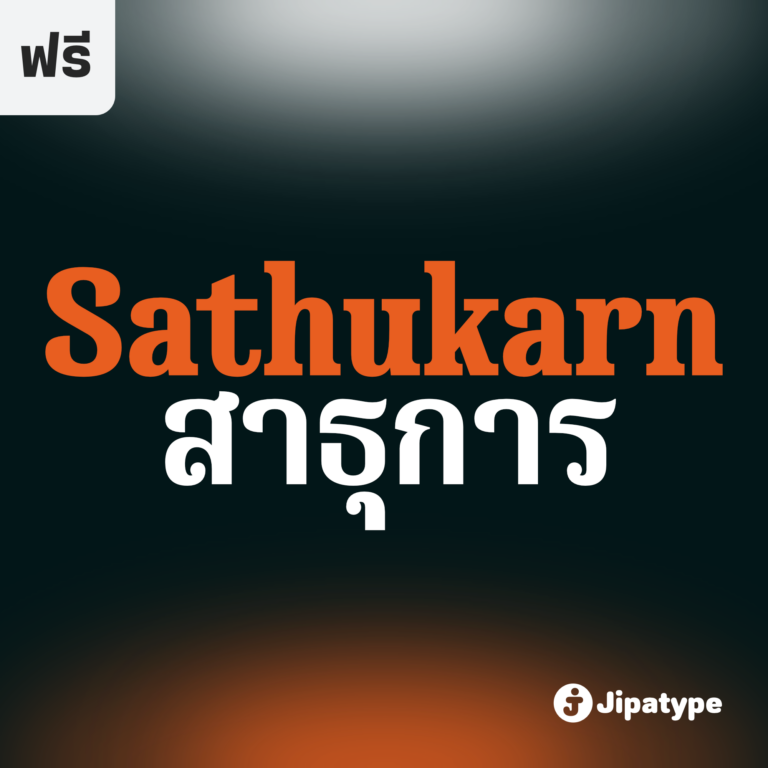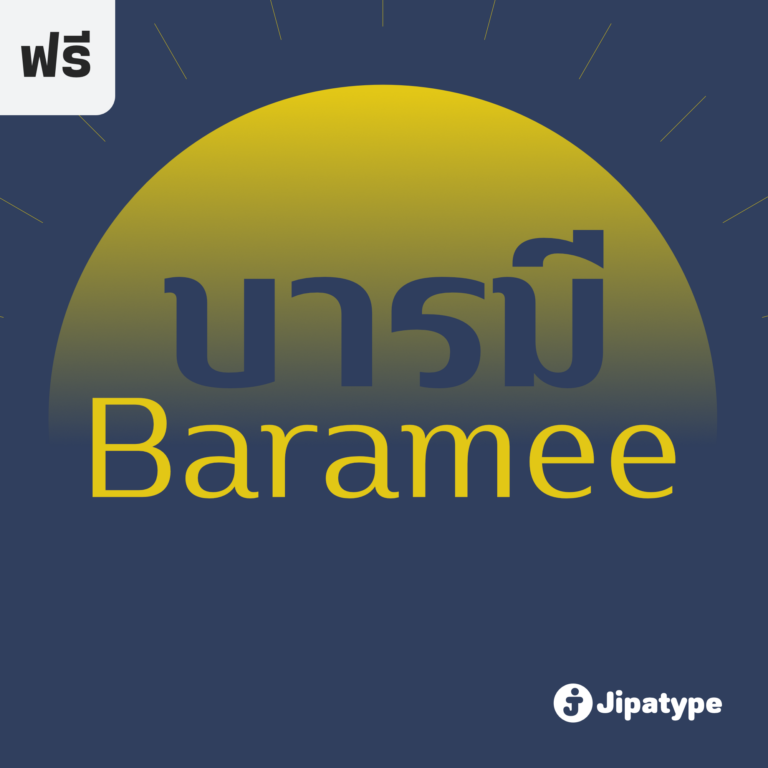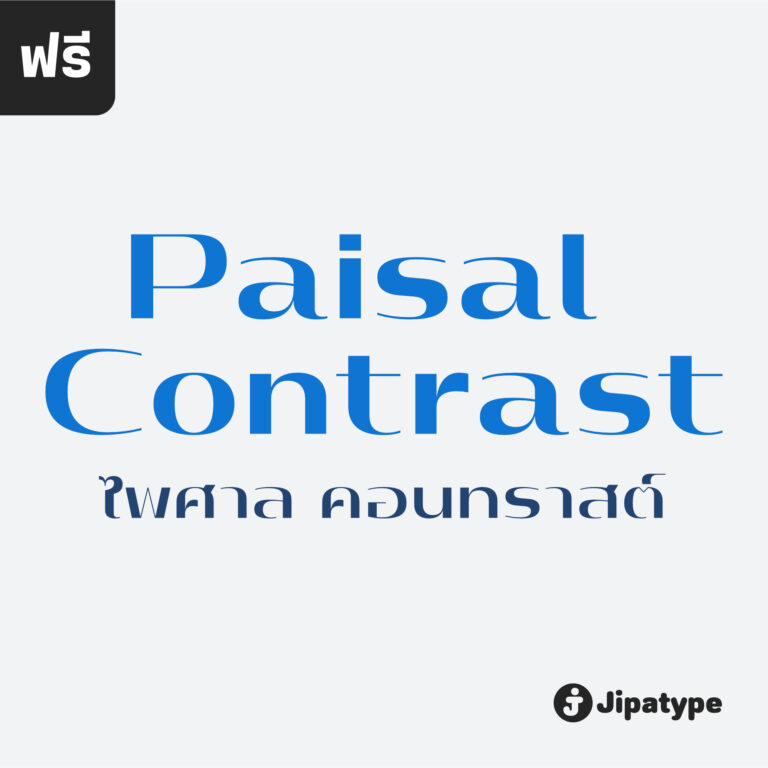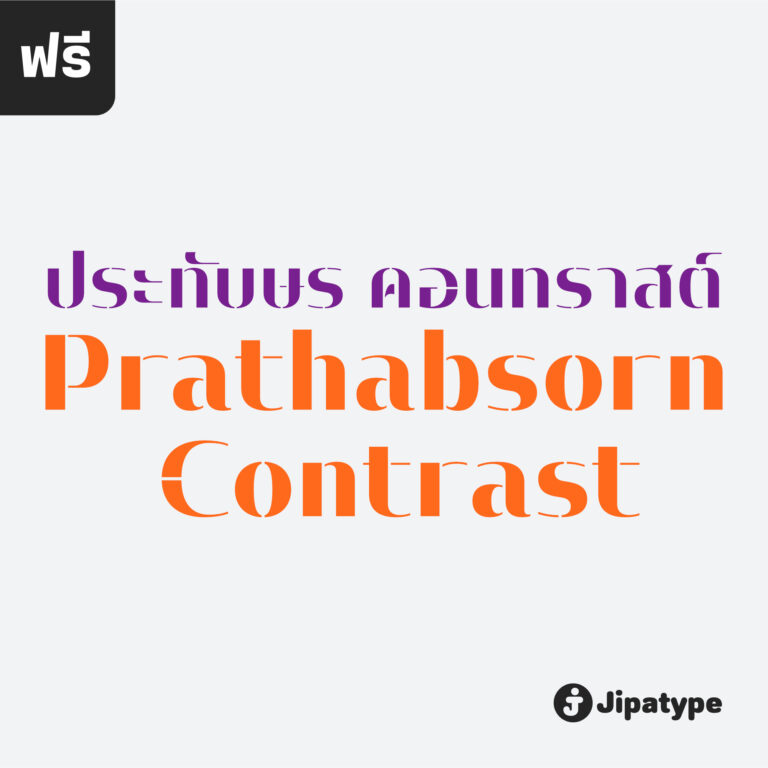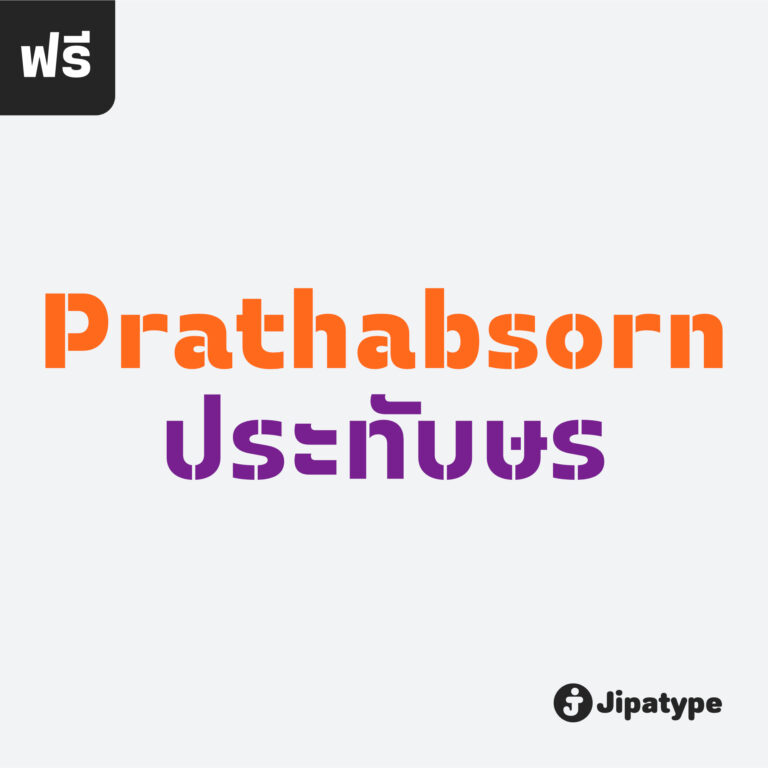
ทวิลักษณ์ เซอริฟ | Thawilak Serif
ขอแนะนำ Thawilak Serif แบบอักษรที่สวยงามและละเอียดอ่อนที่รวบรวมแก่นแท้ของความสง่างาม และความมั่นคง ด้วยคอนทราสต์สูงและรูปทรงที่กว้าง ฟอนต์นี้มีเสน่ห์เหนือกาลเวลาซึ่งจะสร้างความประทับใจให้กับผู้พบเห็นได้ไม่รู้ลืม Thawilak Serif คือตัวแทนแห่งความงามและความมั่นคง ไม่ว่าจะใช้ในสื่อสิ่งพิมพ์หรือสื่อดิจิทัล จะเพิ่มสัมผัสของความมีระดับและความน่าเชื่อถือให้กับโปรเจกต์ต่างๆ ไม่ว่าจะเป็นบทความ การสร้างแบรนด์ หรือบรรจุภัณฑ์ที่หรูหรา ออกแบบโดย : อานุภาพ ใจชำนาญ (Anupap Jaichumnan)สามารถทดลองใช้เวอร์ชันฟรีผ่านแอปฯ ของจิปาไทป์ได้ในเชิงพาณิชย์ ดูรายละเอียดและดาวน์โหลดแอปฯได้ที่ : jipatype.com
ทวิลักษณ์ สลับ | Thawilak Slab
ขอแนะนำ “Tawilack Slab” ฟอนต์ serif แบบ slab ที่แสดงถึงความแข็งแกร่งและความมั่นคง ทวีลักษณ์ สลับ มีรูปทรงกว้าง แข็งแรงและมั่นคง คอนทราสต์ต่ำทำให้เกิดความกลมกลืนระหว่างเส้นหนาและเส้นบาง ทำให้ได้แบบอักษรที่สวยงามและอ่านง่าย ด้วยรูปลักษณ์ที่โดดเด่น ทวีลักษณ์ สลับ จึงสมบูรณ์แบบสำหรับโปรเจกต์ที่ต้องการความชัดเจนและมั่นใจ ไม่ว่าจะใช้พาดหัว หรือสร้างแบรนด์ Thawilack Slab ก็สร้างความประทับใจได้ไม่รู้ลืมด้วยรูปลักษณ์ที่แข็งแกร่งและมั่นคงดึงดูดความสนใจ แบบอักษรนี้เป็นตัวเลือกอเนกประสงค์ที่สามารถปรับเข้ากับบริบทการออกแบบต่างๆ ได้อย่างลงตัว ทำให้เป็นคู่หูที่ยอดเยี่ยมสำหรับทั้งสิ่งพิมพ์และสื่อดิจิทัล ออกแบบโดย : อานุภาพ ใจชำนาญ (Anupap Jaichumnan)สามารถทดลองใช้เวอร์ชันฟรีผ่านแอปฯ ของจิปาไทป์ได้ในเชิงพาณิชย์ ดูรายละเอียดและดาวน์โหลดแอปฯได้ที่ : jipatype.com
หินนวล | Hinnual
Hinnual เป็นฟอนต์ที่ผสมผสานระหว่างรูปทรงสี่เหลี่ยมและทรงกลมเพื่อสร้างสไตล์ที่ไม่เหมือนใคร ชื่อมาจากคำไทย 2 คำ คือ Hin แปลว่า หิน และ Nual แปลว่า อ่อน ผสมผสานองค์ประกอบที่แข็งและอ่อนนี้สะท้อนให้เห็นในแบบอักษร ซึ่งมีเส้นที่สะอาดตาและเส้นคมซึ่งถูกทำให้อ่อนลงด้วยมุมโค้งมน ฟอนต์มีให้เลือกถึง 18 แบบ มีตัวเลือกหลากหลายให้คุณได้เลือกใช้ Hinnual เหมาะอย่างยิ่งสำหรับใช้ในพาดหัวและพาดหัวย่อย ซึ่งลักษณะที่โดดเด่นสามารถช่วยดึงดูดความสนใจของผู้อ่านได้ เส้นสายที่สะอาดตาและสไตล์ที่เป็นเอกลักษณ์ยังทำให้เป็นตัวเลือกที่ยอดเยี่ยมสำหรับแบรนด์ โลโก้ และงานออกแบบอื่นๆ ที่ต้องการภาพลักษณ์ที่น่าจดจำ โดยรวมแล้ว Hinnual เป็นฟอนต์อเนกประสงค์และสะดุดตาที่ผสมผสานองค์ประกอบทั้งความแข็งแกร่งและความนุ่มนวล การออกแบบที่เป็นเอกลักษณ์ทำให้เป็นตัวเลือกที่ยอดเยี่ยมสำหรับนักออกแบบที่ต้องการสร้างผลงานที่น่าจดจำ ออกแบบโดย : อานุภาพ ใจชำนาญ (Anupap Jaichumnan)สามารถทดลองใช้เวอร์ชันฟรีผ่านแอปฯ ของจิปาไทป์ได้ในเชิงพาณิชย์ ดูรายละเอียดและดาวน์โหลดแอปฯได้ที่ : jipatype.com